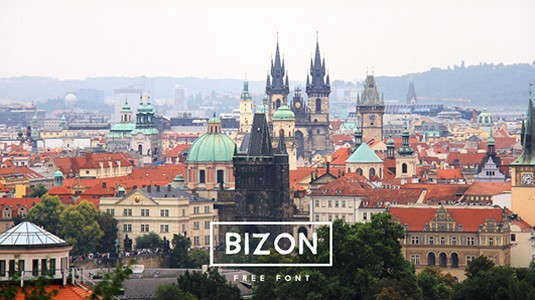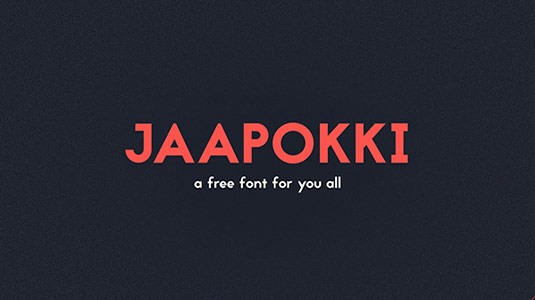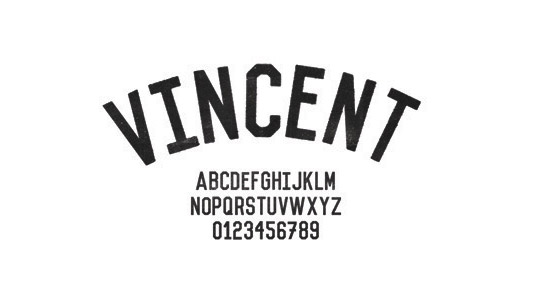
1. Manifiesto
tipografía manifiesto
Una tipografía inspirada en un movimiento racional italiano, que te aporta frescura y sencillez a tus proyectos personales.
2. Vincent
vincent
Ya son más de 300,000 mil personas que han utilizado estas letras para sus logos, cartelería, imagen, etc.. ¿Quieres probar como serían tus  logos con esta tipografía?
3. Bizon
tipografía Bizon
Diseñada y compartida por Fago Studio, esta tipografía es una combinación perfecta entre tipos de letra sans-serif y scrip. ¡Es totalmente gratuita!
4. Jappokki
tipografía jaapokki
5. Streetwear
tipografía caffelatte
Streetwear es una tipografía con aires retros adecuado para logotipos, carteles, estampación textil y mucho más. Está ligada con la moda de los años 60 y 70 relacionada también con el deporte de la epoca.
6. Blow Brush
Free fonts: Monthoers
Es una fuente manuscrita estilo marcador inspirada en el baile hip-hop y la cultura urbana. Aporta dinamismo y a la vez un toque de rebeldía a tus diseños, recordando un poco a los «Grafittis». Tus diseños quedarán auténticos y a la vez formales.
7. Carioca
Free fonts Rex
Estas letras nos ha gustado mucho, ya que nos transmite el «buen rollo» que todos esperamos un sábado por la mañana. Creada por Tano Veron y Yai Salinas, dos diseñadores gráficos argentinos que decidieron crear esta fantástica tipografía gratuita para tus diseños.